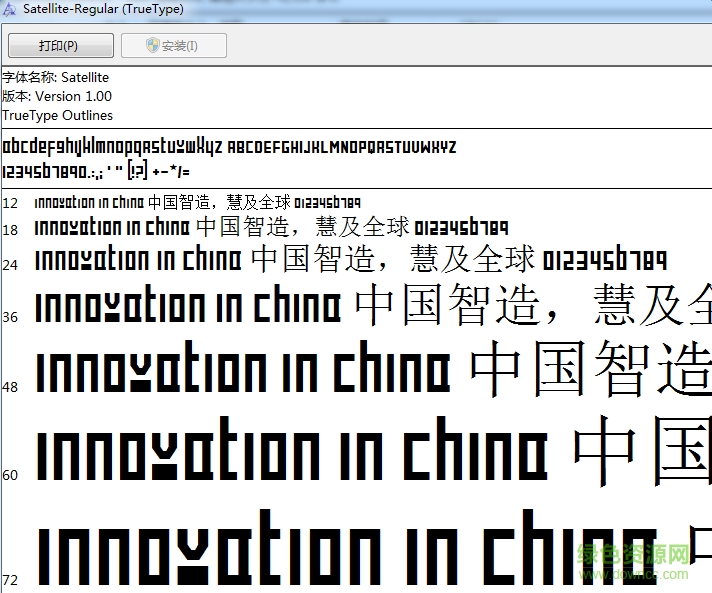
satellite英文字體
satellite字體是一款英文字體庫中的個(gè)性字體,字體的整體效果非常出色,可以廣泛應(yīng)用于出版印刷、文學(xué)雜志、宣傳海報(bào)、ppt、影視制作以及任何使用文字的領(lǐng)域,有需要的朋友可以免費(fèi)下載收藏。
satellite字體
satellite字體是英文字體庫中的一款極具個(gè)性的字體,該字體的形體非常飄逸,給人大氣的感覺。適用于美工設(shè)計(jì),有需要的用戶可以來綠色資源網(wǎng)下載使用!